别再写丑名字了!教你一键解锁姓名艺术签名设计
不管是商务合同上的落款、社交账号的个性标识,还是手写贺卡的收尾,一款好看又贴合气质的姓名艺术签名,总能悄悄加分。很多人觉得做艺术签名得有书法功底、会设计软件,其实不用这么麻烦——用好在线艺术字体生成器,零基础也能快速搞定你的专属艺术签名。今天就把我实测过的4款宝藏工具分享给大家,一步步教大家打造专属签名。
一、字由网
说到艺术字体和签名设计,那字由网绝对是我最常使用的一款,做姓名艺术签名更是兼顾便捷度和质感,新手闭眼冲也不踩雷,也是这次的首选推荐。
之前我们可以用字由网的手写字体来做姓名艺术签名,比如我用过的点字晨颜行楷、汉仪半舫家书w、汉仪国强行书等。这些字体在客户端都可以激活使用,操作也非常简单,在自有客户端直接搜索字体名称即可,但要注意是否免费商用哦~
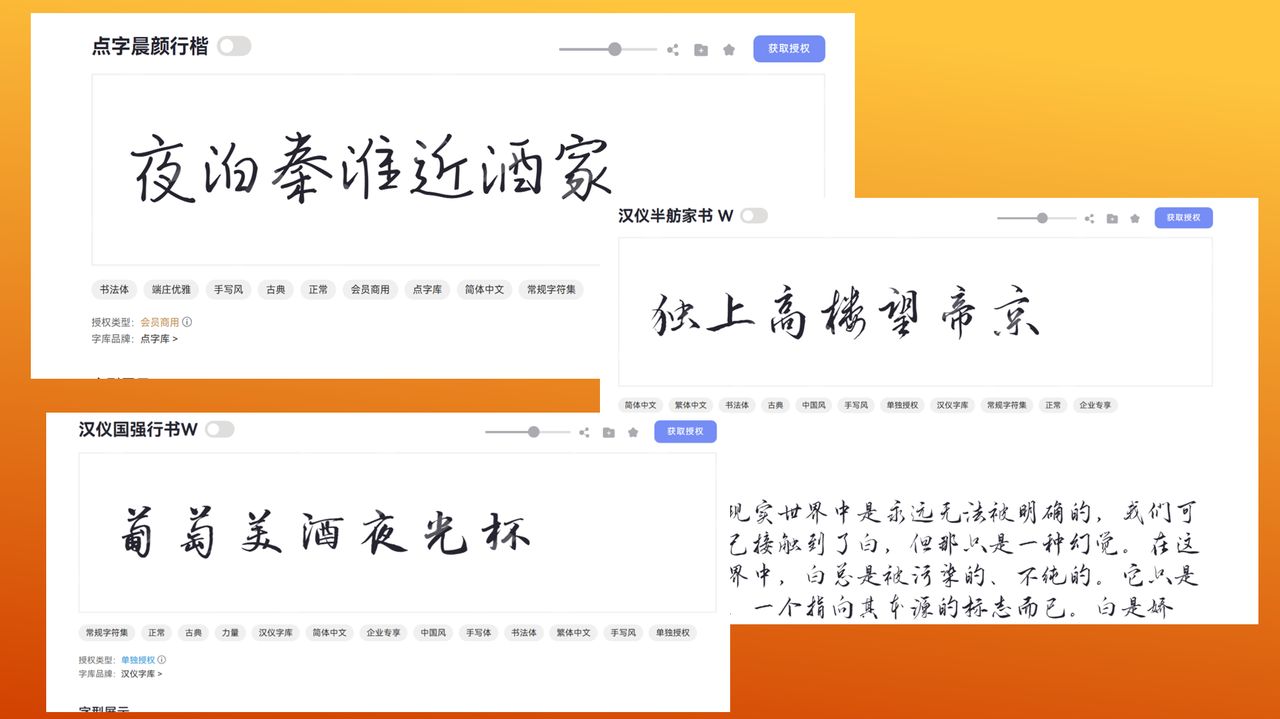
当然如果大家还想要更个性一点的艺术签名,字由网也有很多字体可供大家挑选,你总能找到一款适合你能够代表你身份的字体来设计你的姓名艺术签名,甚至能找到贴近手写质感的笔触字体,日常办公、正式场合都能匹配。
不过,最近字由先上线的“AI字体”更方便大家打造姓名艺术签名了,对新手太友好了。如果想更贴近手写体风格,可以直接在风格分类中选择“手写体”。还有很多风格类型,方便大家直接挑选。
选择好自己喜欢的模板后,在右侧的文本框内输入自己的姓名,点击立即生成等待几秒,就能得到自己的专属姓名艺术签名啦。一键就能下载高清图,打印、存手机当电子签名都能用。
二、万字网
万字网是一款主打书法风格的宝藏工具,兼顾艺术字体生成与书法学习功能,堪称“在线书法字典+签名神器”,尤其适合偏爱毛笔风、楷书风签名的用户。万字网有专门的签名字体,无论是中文签名还是英文签名,这里都有。操作流程简洁不繁琐:进入官网后直接定位“签名字体”专区,输入姓名后,可选择字体大小和颜色,点击在线转换就可以得到你的姓名艺术签名。
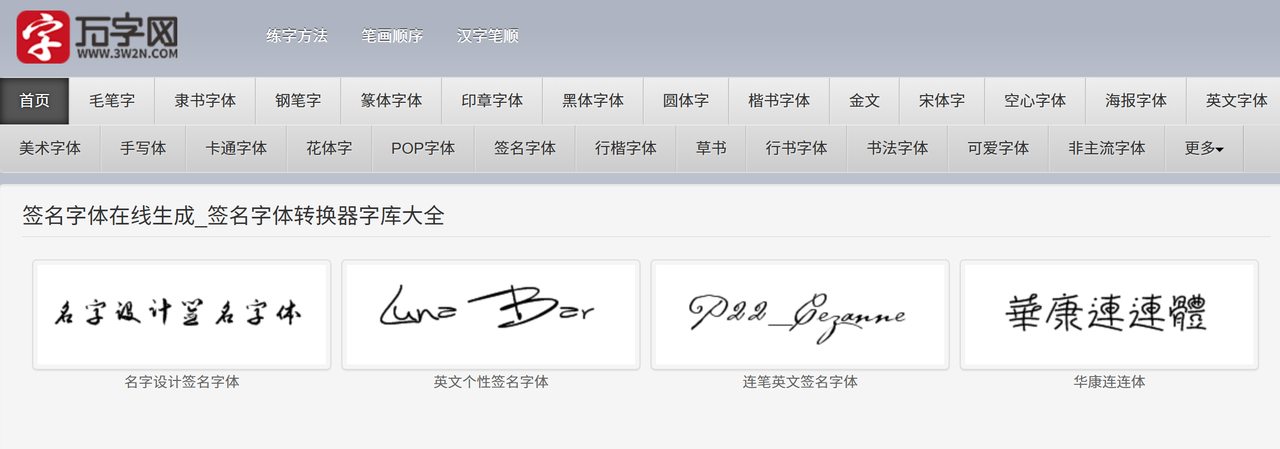
三、艺术字网
如果你追求签名的视觉冲击力,不想局限于传统字体,艺术字网绝对是首选。打开网页无需注册,选择菜单栏的“签名字,”直接在输入框键入姓名,你可以选择要生成的字体,系统会自动生成基础艺术字体,随后可进入特效设置界面,一键添加渐变颜色、文字倒影、立体效果等,无需手动调试,新手也能做出高级感。
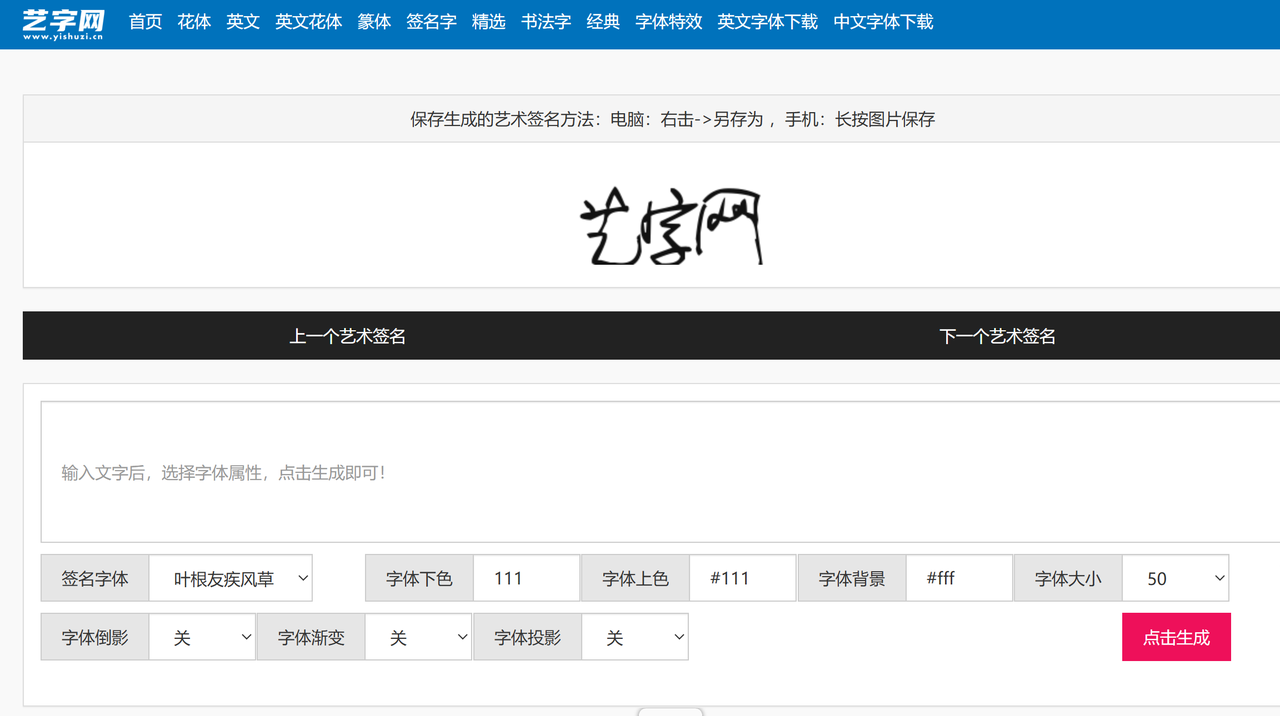
四、字体天下
字体天下是一款综合性的字体服务网站,既有适合新手的免费艺术字体生成功能,也有正版商用字体资源,兼顾实用性和安全性,适合需要兼顾个人使用与商用场景的用户,姓名签名设计功能兼顾简洁与多样。跟字由网相似,大家可以选择喜欢的字体进行设计签名,也可以找到“在线艺术字体生成”板块,输入姓名后,可筛选简约、复古、卡通、英文搭配等多种风格,字体覆盖常用的签名样式,能满足日常个人使用需求。
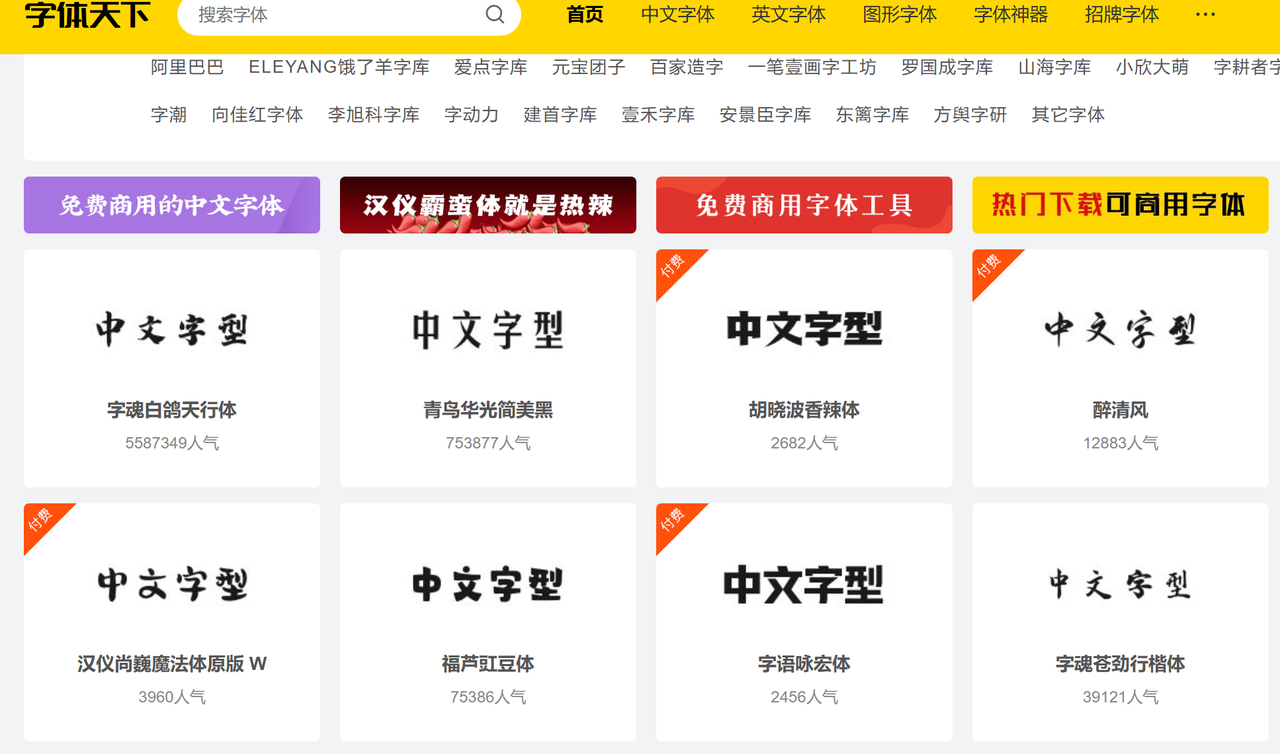
以上四款艺术字体生成器,无需专业书法功底,无需复杂设计软件,只需几步操作,就能生成贴合自身气质、适配场景的艺术签名。职场人可打造利落商务签名,提升专业感;年轻人可解锁个性特效签名,彰显潮流态度;书法爱好者可深耕毛笔风签名,传递文化质感;创作者可借助商用合规工具,搞定文创、品牌相关的签名设计。